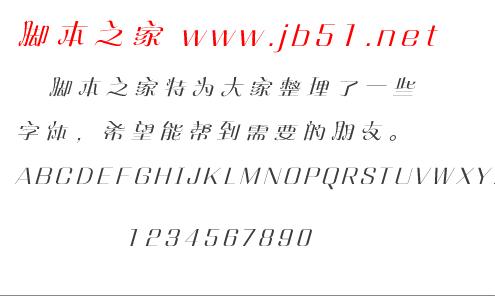
方正飛逸體創(chuàng)意靈感來(lái)源于藝術(shù)體操運(yùn)動(dòng)中的帶操運(yùn)動(dòng),運(yùn)動(dòng)員揮舞手中的絲帶,動(dòng)作柔軟、流暢、飄逸、優(yōu)美,由此設(shè)計(jì)出帶有靈動(dòng)飄逸,自信飛揚(yáng)的飛逸體,適合運(yùn)用于各種包裝宣傳設(shè)計(jì)。